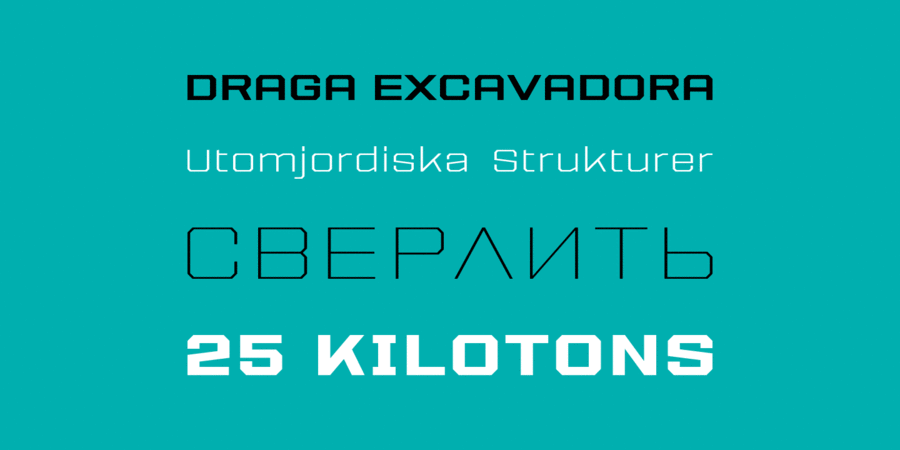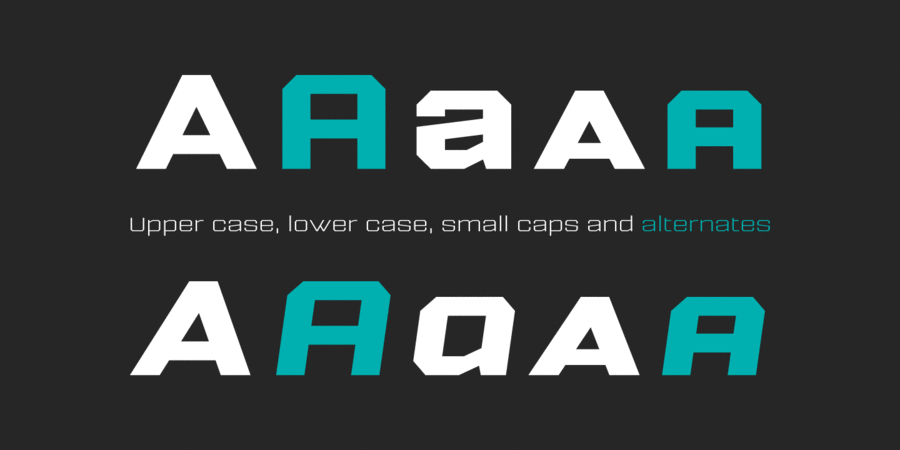
Опис гарнітури TuercaГарнітура Tuerca – це трохи розширений паличний гротеск із суворим техногенним виглядом. Його квадратні кутасті форми мають футуристичний та надійний вид. Цей шрифт був задуманий для логотипів, заголовків і акціенціі, а також для коротких текстових блоків. Tuerca складається з 8 накреслень. Кожне містить гліфи для латиниці й кирилиці, капітель, лігатури. Шрифт розробив Пабло Балселлс в 2021 році.
Асоціації з сімейством шрифтів TuercaОсобистість і характер гарнітури:
рівний, квадратний, точний, логічний, холодний, автоматичний, техногенний, твердий, статичний, різкий, чіткий, стійкий, стабільний, тонкий, легкий, прямокутний, міський, сучасний, машинний, гострий, інженерний, урбаністичний, креслярський, скляний, крихкий, футуристичний, дротяний, Простий, надійний, впевнений, сталевий, космічний, байдужий, гранчастий, рубаний, переконливий, серйозний, сильний, індустріальний, залізний, мужній, військовий, армійський, промисловий, залізничний, ігровий, наполегливий, спортивний, робочий, кінематографічний
конструктор, креслення, архітектура, інженер, автоматика, урбаністика, наука, дизайн, Місто, статистика, гаджет, електроніка, технології, фантастика, космос, інструмент, робот, гра, прилад, айтішник, IT, айті, андроїд, залізо, коворкінг, рентген, авто, промисловість, війна, армія, зброя, завод, металургія, верстат, тара, склад, порт, ящик, патрони, техніка, ремонт, депо, шолом, уніформа, вагон, авіація, літак, автомат, шутер, екшен, транспорт, страйкбол, взуття, залізниця, кубики, лего, комп'ютерна гра, спорт, машинобудування, охорона, захист, паливо, поліція, будівництво, цегла, автобус, робочий, кіно, кіберспорт Гарнітура асоціюється з віком: